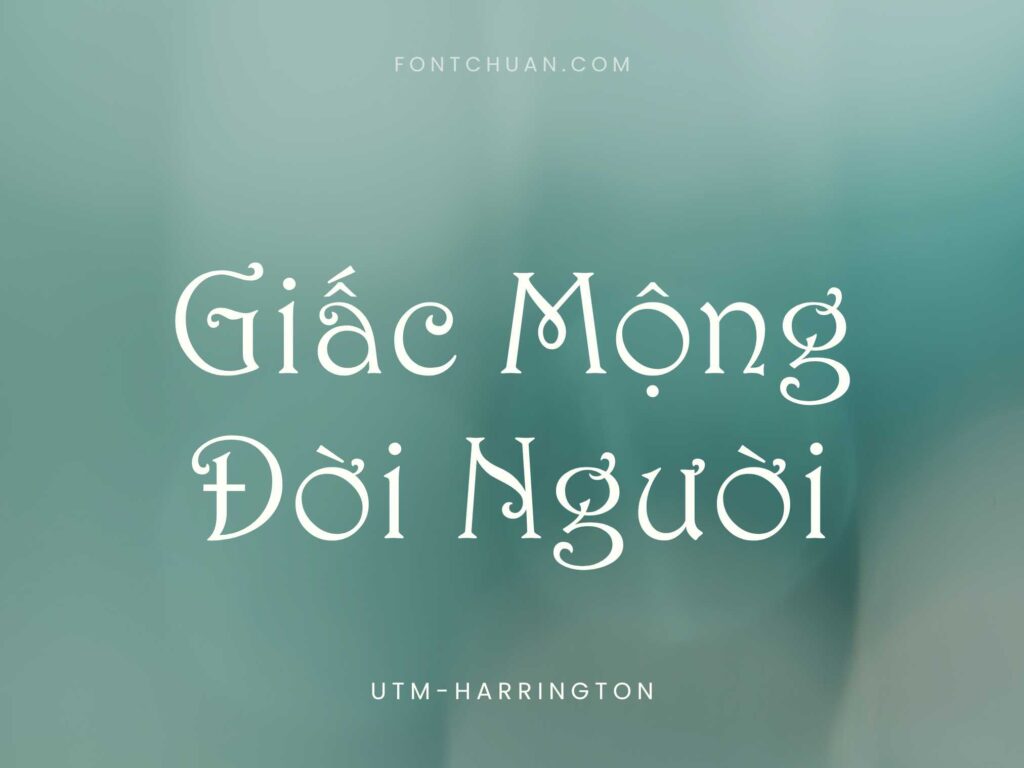
Font UTM Harrington Việt Hóa
UTM Harrington là một font chữ mang phong cách cổ điển với những đường nét uốn lượn mềm mại, gợi lên sự thanh lịch và sang trọng. Font này được thiết kế để mang đến sự tinh tế trong các ứng dụng đồ họa và thiết kế thương hiệu. Font đã được Việt hóa bởi Thiên Minh, hỗ trợ đầy đủ tiếng Việt cùng hơn 200 ngôn ngữ khác, giúp mở rộng khả năng sử dụng. Thành viên của Font Chuẩn đã sưu tầm và giới thiệu font này nhằm đáp ứng nhu cầu bạn đọc, cung cấp nguồn tham khảo chất lượng và ứng dụng thực tế vào các dự án thiết kế
Về đặc điểm thiết kế, UTM Harrington có các nét chữ cong tròn, độ tương phản vừa phải và phong cách mềm mại. Font này phù hợp với nhiều ứng dụng như thiết kế logo, thiệp mời, biển hiệu, tiêu đề trang web và các ấn phẩm sáng tạo. Các ngành nghề như quảng cáo, ẩm thực, thiệp cưới và giáo dục có thể tận dụng font này để tạo điểm nhấn và mang đến sự sang trọng trong các sản phẩm thiết kế